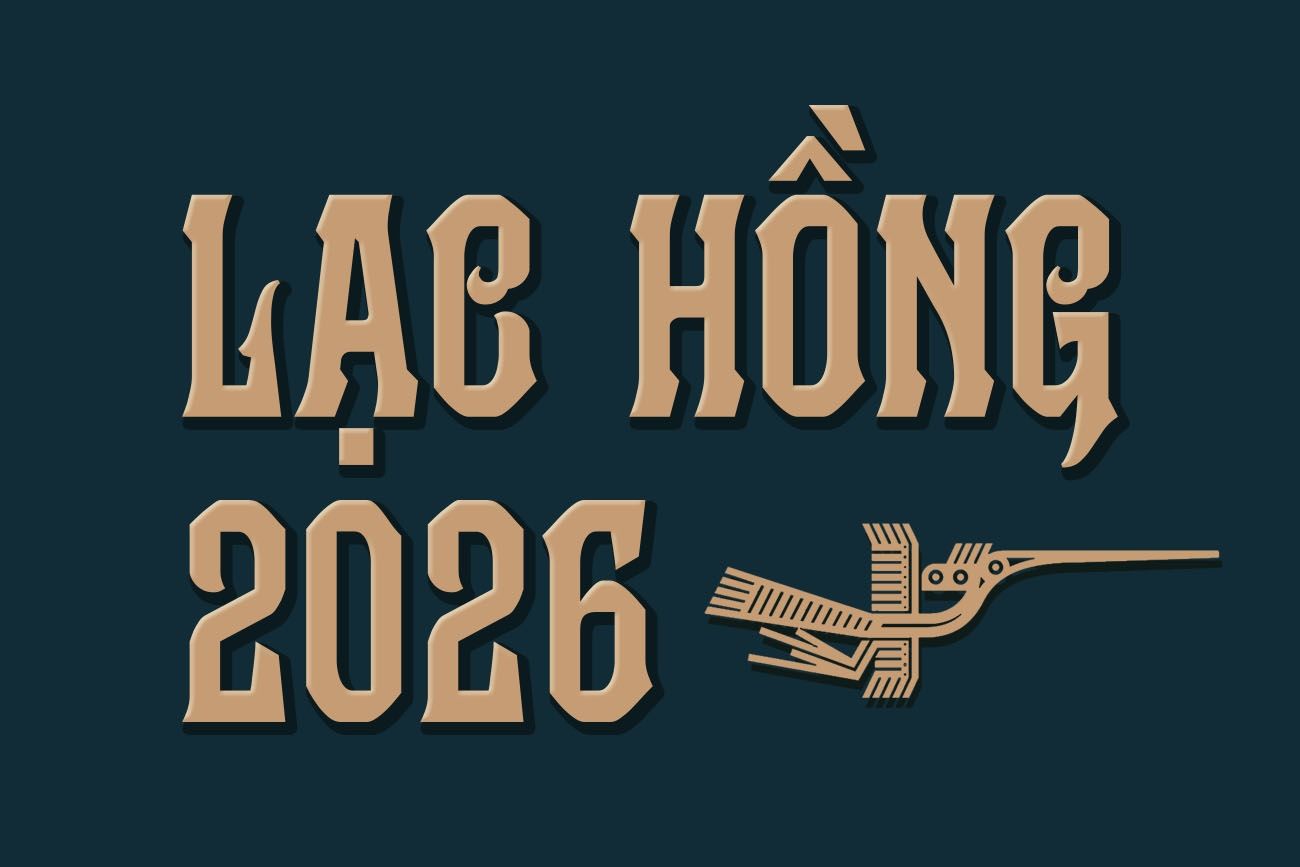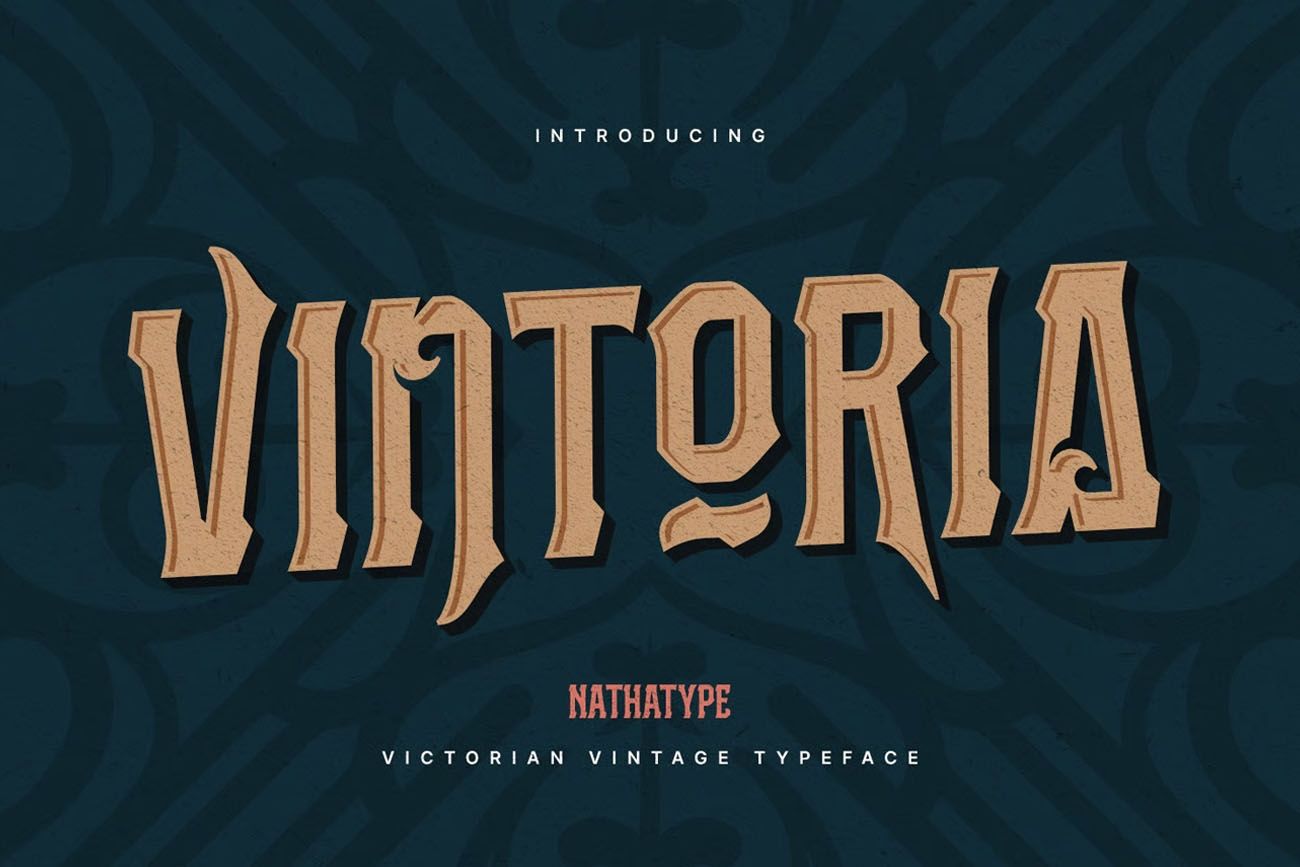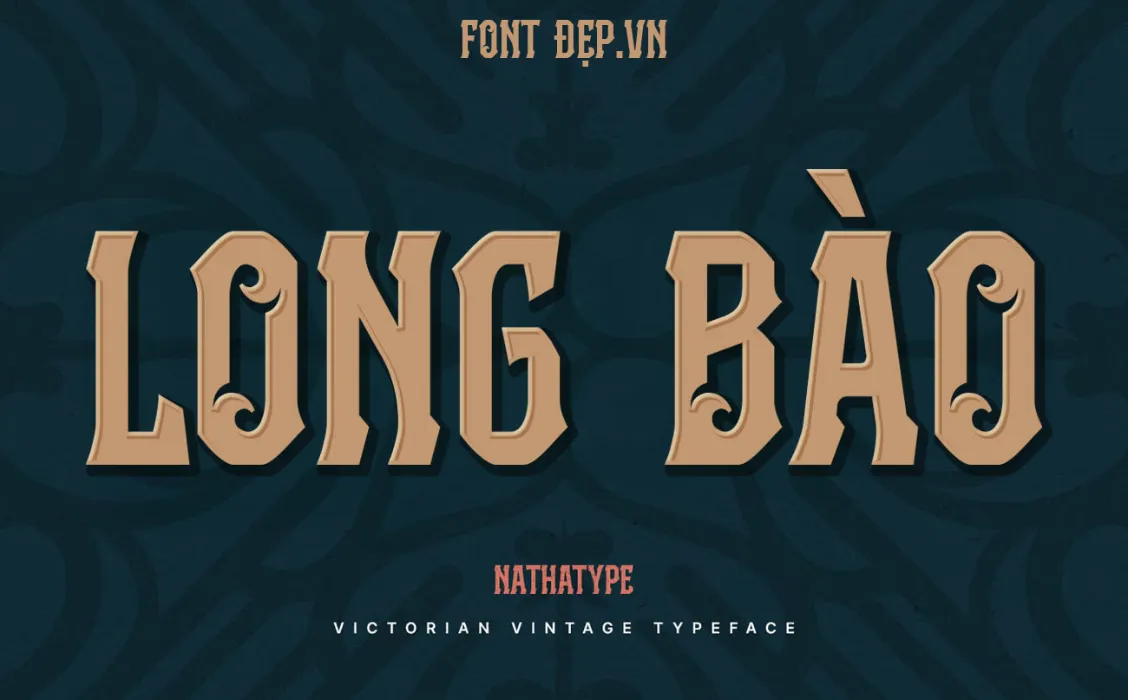
Nếu bạn đang tìm kiếm một sự giao thoa hoàn hảo giữa nét hoài cổ thập niên cũ và sự xa hoa của cung điện, TH Vintoria Việt hóa chính là câu trả lời. Đây là dòng phông chữ Serif được thiết kế với những đường nét thanh mảnh, dứt khoát nhưng không kém phần uyển chuyển, mang đậm hơi thở Vintage Hoàng gia đầy quyền quý.
TH Vintoria gây ấn tượng mạnh bởi bộ chữ cái được chăm chút tỉ mỉ, tạo cảm giác như những bản in thủ công trên giấy da cao cấp. Bản Việt hóa đã được tối ưu hóa hoàn toàn, giúp các dấu tiếng Việt giữ được sự tinh tế, không làm phá vỡ cấu trúc sang trọng vốn có. Font chữ này là lựa chọn thượng hạng cho các thiết kế:
Logo thương hiệu cao cấp: Thời trang, nước hoa, hoặc trang sức.
Menu nhà hàng Âu: Tạo không gian ẩm thực cổ điển và chuyên nghiệp.
Bìa tạp chí nghệ thuật: Khẳng định đẳng cấp và gu thẩm mỹ tinh tường.
Với TH Vintoria, mỗi dòng chữ viết ra đều trở thành một tác phẩm nghệ thuật, mang đến vẻ đẹp vượt thời gian cho mọi dự án của bạn.